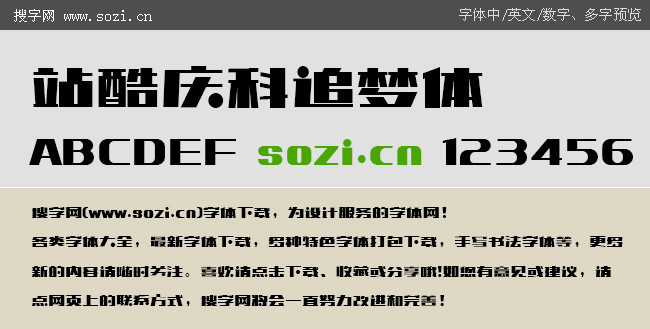
站酷慶科追夢體
搜字網(wǎng)提供一款站酷慶科追夢體中文字體下載,站酷慶科追夢體是一款由站酷開發(fā)的一款中文中文藝術(shù)字體,這款字體筆觸較為粗實,字體稱扁平狀態(tài),適合應(yīng)用于藝術(shù)設(shè)計、平面宣傳設(shè)計、網(wǎng)頁設(shè)計,書法字帖等領(lǐng)域。(此款為個人非商用版,如需商用請聯(lián)系作者購買)